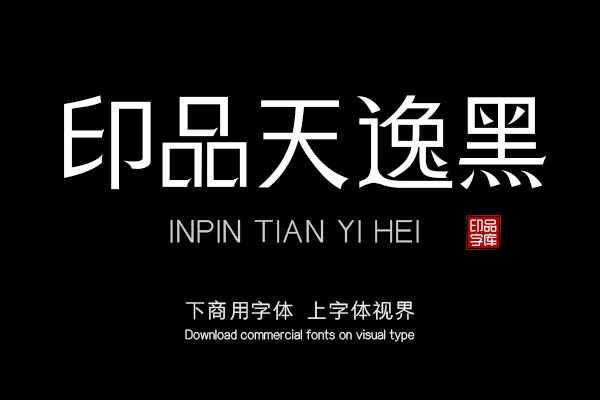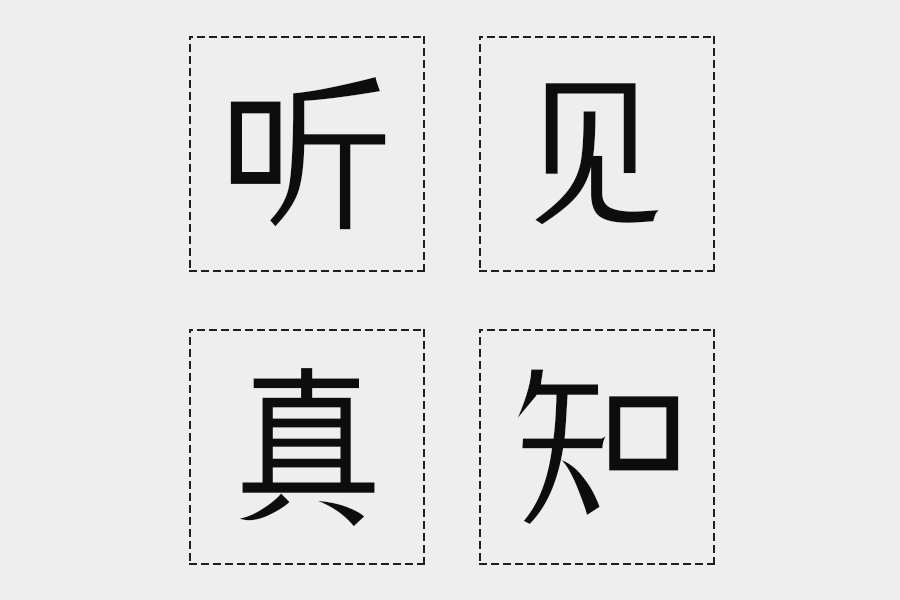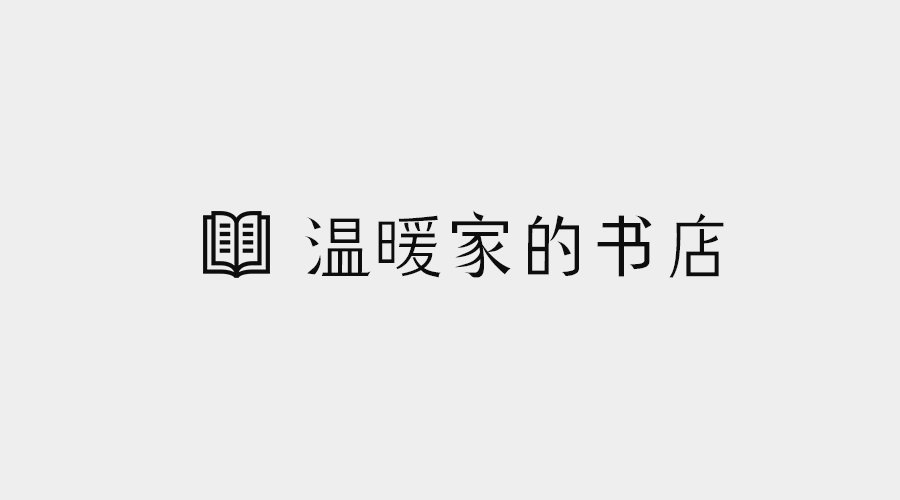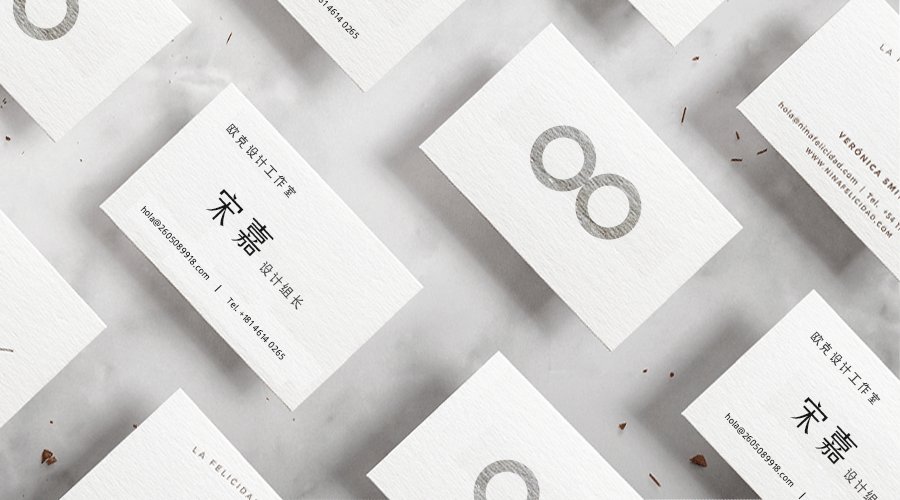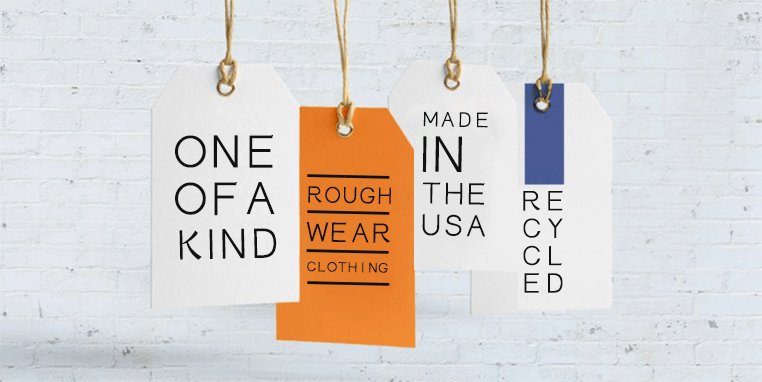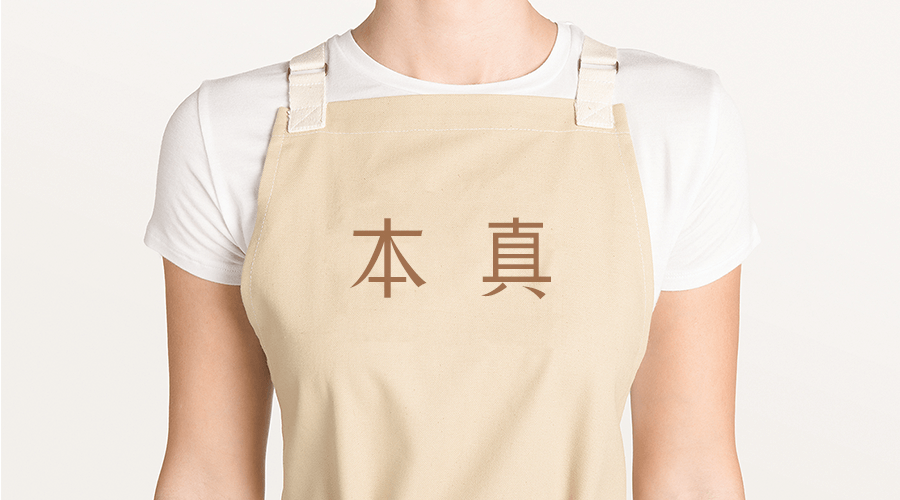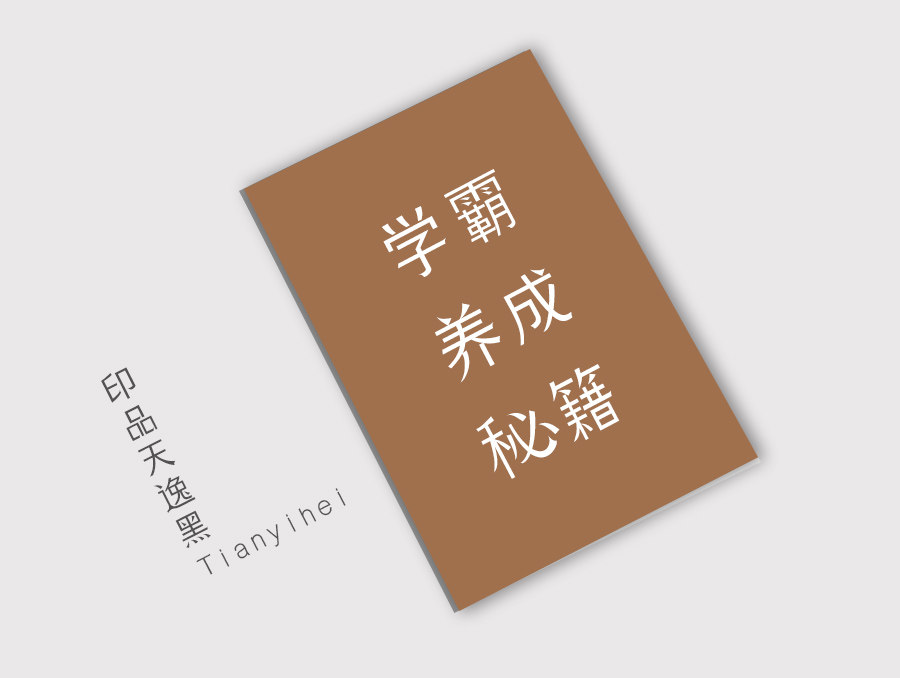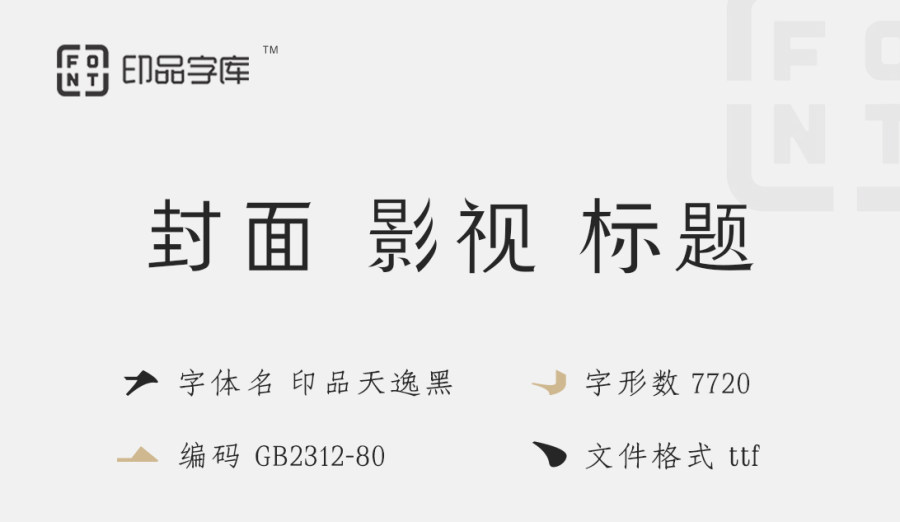
• 印品天逸黑
• 印品天逸黑字形笔画整齐划一,简洁大方,横竖笔画基本上保持一致,个性鲜明,引人注目。字体结构严谨端庄,字形饱满,硬朗的笔划赋予其力量感,整体风格刚劲有力而又不失俊儒之风,凸显出精简精干的特点,其笔画之中蕴含古朴沉厚端凝之势,印品天逸黑整体朴素大方、笔画单纯、结构严谨,引人注目、实用性强,正文、注释、小标题。